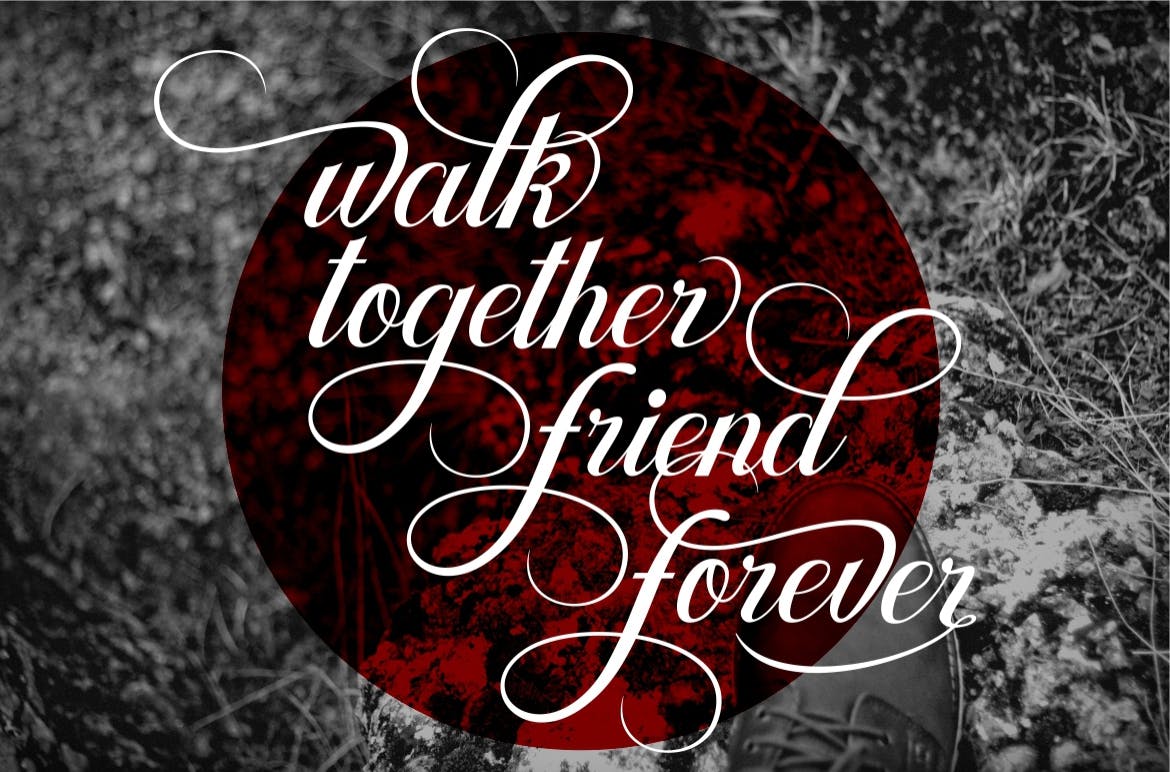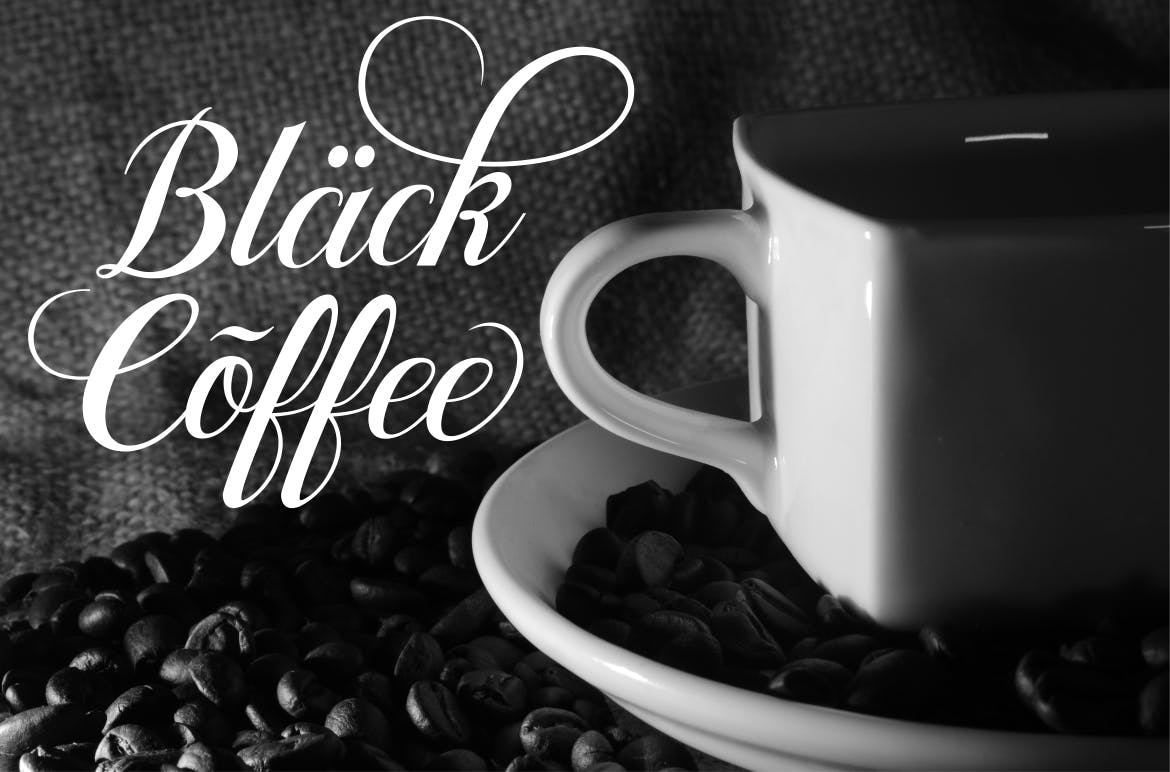
فونت Gullever بهگونهای طراحی شده است که یک فونت زیبا و مناسب باشد. انحناها و خطوط نرم این فونت، آن را به گزینهای جذاب تبدیل کرده است. این فونت بهطور ویژهای مناسب برای تمامی پروژههای طراحی شما از جمله کارت دعوت، لوگو محصولات، لوگو برندهای غذایی و بسیاری موارد دیگر است.
فونت Gullever همچنین با کاراکترهای اضافهای که شامل : لیگاتورهای استاندارد، سوآشها، و مجموعههای استایلی ۰۱ تا ۰۵ پشتیبانی میشود.
این ویژگی به شما کمک میکند تا با خلاقیت خود، سبک زیبایی را ایجاد کنید.